Das London-2012-Logo: Ein Fazit
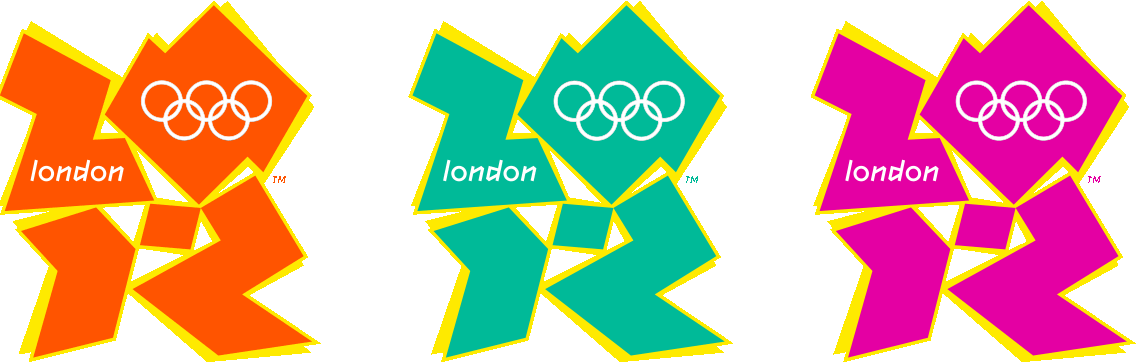
Was wurde geschimpft und gelästert über das Londoner Olympia-Logo, als es am 4. Juni 2007 erstmals vorgestellt wurde (Fontblog berichtete: Das Olympia-Logo 2012 ist für alle da). Bereits ein Tag später habe ich das freie Konzept (das 1 Jahr später verworfen wurde) hier im Fontblog verteidigt: London 2012 will doch nur spielen. Die Debatten waren heiß und spannend, führten aber nicht weiter. Daher lautete mein Fazit am 11. Juni 2007 »Freiheit nicht erwünscht … Designer mögen es eher diktatorisch«. Diskussion beendet.
Zu den stärksten Kritikern der London-2012-Identity gehörte die britische Designpresse, allen voran Creative Review und Design Week. Letztere feiert das einst »Scherbenlogo« getaufte Signet heute als Design-Ikone (London 2012 design icons – the Olympic logo) und schreibt wörtlich: »Klug, energiegeladen und leicht unpraktisch … es reflektiert London.« Nur Schade, heißt es weiterhin, dass es über mehrere Jahre »wie eine Briefmarke eingesetzt wurde«, anstatt mit ihm zu spielen. Als einzigen Ableger der Ursprungsidee erinnert das Magazin an ein adidas-Video von Matt Pyke (Universal Everything), das vor 3 Jahren entstand:
Creative Review wirbt heute im Blog für seine aktuelle Print-Ausgabe, in der sich Adrian Shaughnessy ausführlich mit dem London-2012-Logo und seinen Machern beschäftigt, die erstmals offen über den Entwurfsprozess reden. In einem Vorwort zeigt sich CR-Chefredakteur Patrick Burgoyne versöhnlich: “I still can’t bring myself to love it and I do think that the goals of 2012 could have been achieved with something more appealing. But I absolutely admire the thinking behind what Wolff Olins did for 2012. They set in motion, from the very beginning, a principle that London would reinvent what it means to host an Olympic Games. That principle succeeded brilliantly.”
Fazit: Weniger meckern, mehr wagen, Neues akzeptieren.
Da ich die Olympischen Spiele nur im Fernsehen verfolgen konnte ist mein Fazit: funtionierte nicht.
Im Print vielleicht ein ein tolles Erlebnis, am Fernseher gar nicht erkennbar. Daher ist es für mich durchgefallen.
Insgesamt bin ich –nach dem Ende der Spiele– positiv vom Logo überrascht. Die Tatsache, dass es aussieht, als würden Lisa und Bart Simpson, sagen wir mal, intim, konnte ich zwar nicht aus meinem Kopf verbannen, zusammen mit den Bannern in den Stadien und der (gewöhnungsbedürftigen, aber klar identifizierbaren) Schrift wirkte es auf mich jedoch modern, frisch und irgendwie „londonerisch“.
Was mich persönlich gestört hat, war, dass die Einblendungen im TV (Zeiten, Namen, Tabellen, …) scheinbar nicht an das Design angepasst waren (rund, blau mit Verläufen, Standardschrift, …)
Ausgelöst durch das hier:
haben wir hier das Thema schon kurz diskutiert:
Meine Position:
Ich mochte die Präsentation und das theoretische Konzept des Corporate Designs … ich mag die Elemente und deren Konbinierbarkeit … ich sehe, was 4 Jahre nach der Vorstellung zu erwarten war, dass es visuell tatsächlich schon ein wenig „alt“ wirkt, aber auf seine Art was könnte.
Aber die Umsetzung, wie sie im Fernsehen rüber kommt, ist für mich kläglich gescheitert. Da mal ein einsamer bunter Banner mit ein paar grellen Dreiecken drauf, dort mal nur eine Farbfläche … das „richtige“ Logo ist tatsächlich selten zu sehen, der Schriftzug viel prominenter … generell ist recht wenig „Grafisches“ präsent, oder aber unüberlegt in gewaltigem Übermaß (Hockey- und Turner-Farbrausch), die Maskottchen sind so gut wie gar nicht präsent (aber das scheint irgendwie typisch zu sein dass die im Fernsehen nicht auftauchen), dazu passt dann noch das Sounddesign, bei dem ab und an extrem grell was daher rumpelt.
Vielleicht wirkt das alles vor Ort anders, aber das tolle Konzept kommt per TV einfach nicht rüber.
Athen und Beijing [also die im Fernsehen sichtbaren grafischen Auftritte davon] waren unaufgeregter und für mich trotzdem visuell präsenter und prägender. Vielleicht auch einfach, weil sie in der Umsetzung leichter zu handhaben waren?
Sebastian Nagel
Schade übrigens, dass dann bei der Abschlussfeier die LED-Leuchteffekt-Lichtspiele auf den Tribünen in Helvetica (oder war es gar Arial?) umgesetzt wurden, nicht in der offiziellen Schrift.
André
»Fazit: Weniger meckern, mehr wagen, Neues akzeptieren.«
Ganz genau, Jürgen! Auch in Deutschland ist man scheinbar noch nicht so weit.
Schrägstrich
Weniger meckern …, find ich gut!
Aber kann sich mal jemand der der Trailer von ARD/ZDF annehmen. Das war für mich der totale Grusel. Dazu hätte ich gern mal ne Auswertung/Diskussion.
Hab wenig Olympia geguckt. Bei Tennis und Radfahren fand ich die Screeninfos einfach inhaltlich nicht logisch. Soll heißen es gab die wichtigsten Infos nicht, fand ich. Da schliess ich mich Prente und Sebastian an.
Dominik
Ich fand das Logo letztlich gar nicht so schlecht, bis wir am letzten Tag der Spiele in der Familie darüber diskutierten. Meine Mutter sah im Logo die Umrisse Londons, auch mein Bruder hatte die „2012“ nicht erkannt. Wer weiß, wie vielen Leuten das noch so ging?
Einee
Mein Prof hatte uns das damals gezeigt.
Ein paar Gedankenspiele hin und her:
Fazit: Ich fands super.
@4:
Das On-Air-Design war doch ohnehin in Arial gehalten, oder?
Die Gestaltungsidee finde ich gut, die Gestaltungselemente wirken dagegen auf mich eher muffig und angestaubt. Vllt. liegt es auch an der Kombination mit den Farben und Pseudo-Schatten. Erinnert mich an Briefmarkendesign der 70er.